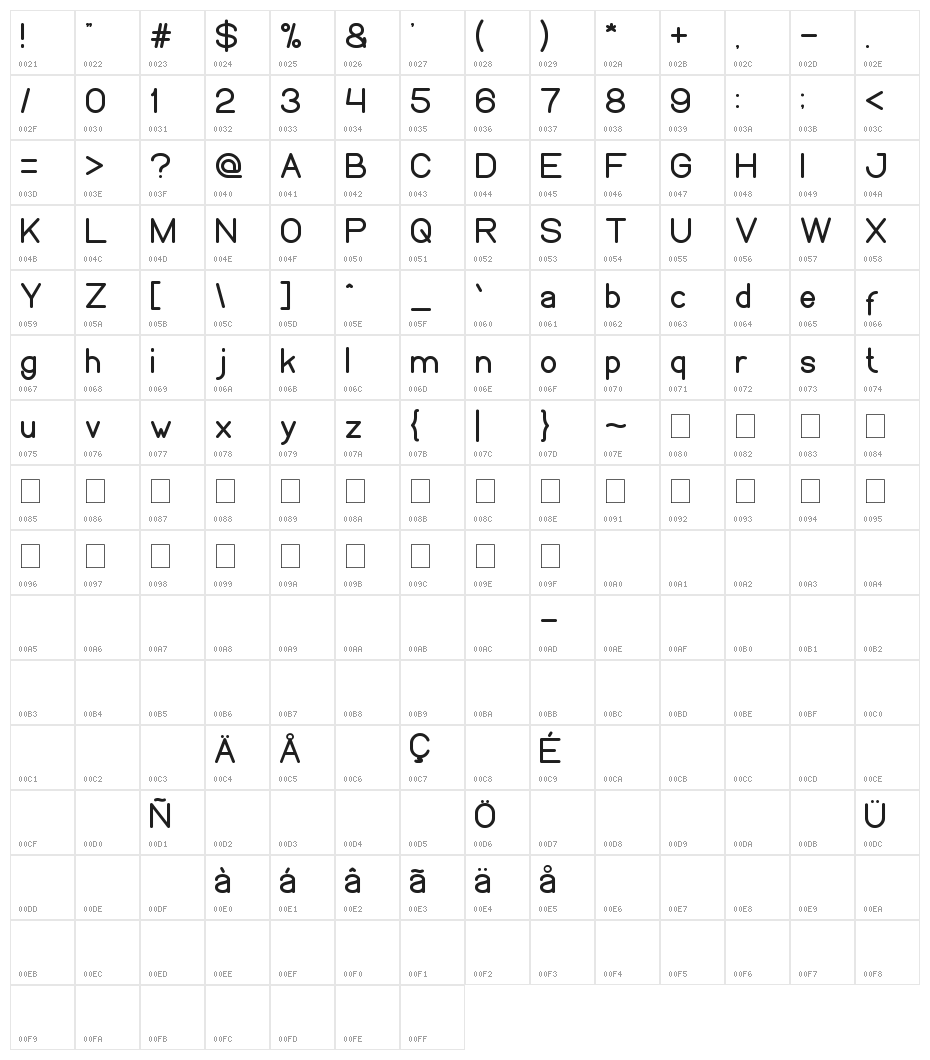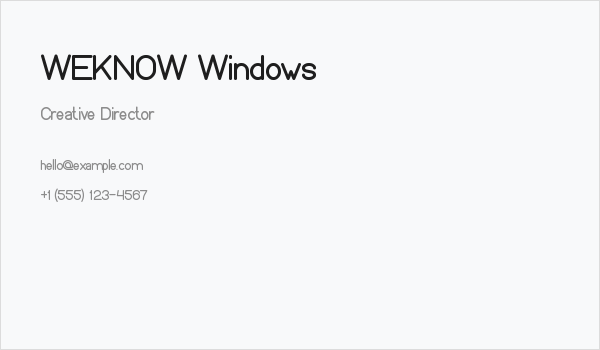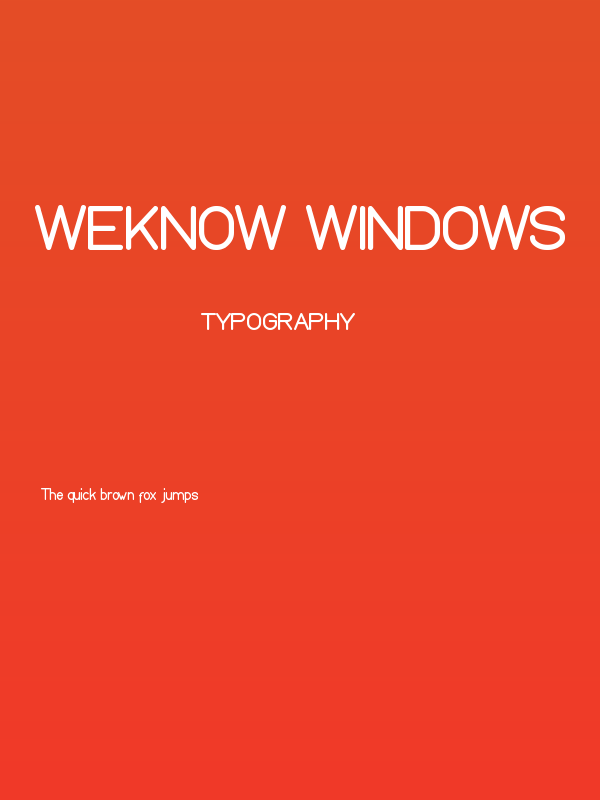
WEKNOW Windows Font
Fonts by weknow - Wino S Kadir
| Progetti proposti | Ideal for digital interfaces, branding, advertising, and signage where a modern and approachable look is needed. |